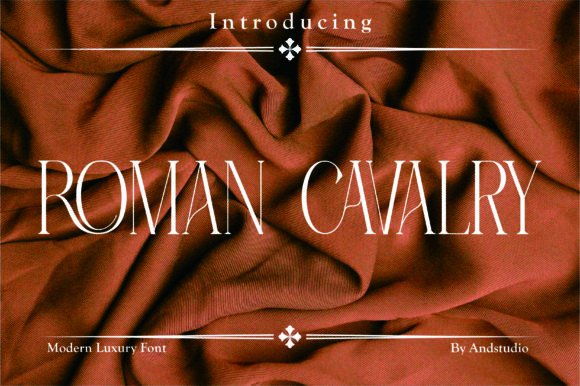
Roman Cavalry
إذا كنت تبحث عن أصول عالية الجودة مثل Roman Cavalry، فإن هذه الحزمة المميزة هي خيار رائع لمشاريعك الإبداعية.
تم تصميمه بدقة، ويوفر Roman Cavalry متجهات نظيفة وطباعة سلسة وترخيصًا تجاريًا لراحة بالك.
سواء كنت تقوم بإنشاء منتجات الطباعة عند الطلب أو دعوات الزفاف أو رسومات وسائل التواصل الاجتماعي، فإن Roman Cavalry هو الخيار المثالي.